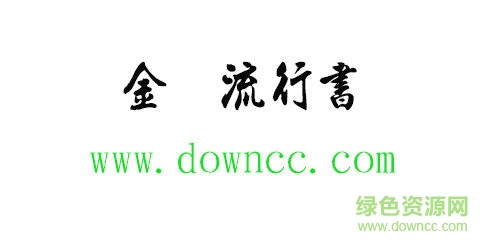
金梅流行書是一款適合于廣告設(shè)計印刷的電腦字體軟件,字體簡潔秀麗,一鍵安裝即刻使用,在你需要使用電腦編輯大量文章信息的時候,不妨使用一下該字體,能夠讓你的字體表現(xiàn)形式更加美觀大方哦,感興趣的可以來本站下載體驗一下。
金梅流行書是金梅字體庫中一種字體,常用于美工設(shè)計方面,喜歡的朋友不要錯過。
1、支持簡體中文和繁體中文。
2、支持網(wǎng)絡(luò)常用中文簡繁。
3、支持西文和數(shù)字。
4、字體風(fēng)格:時尚、現(xiàn)代、可愛、快樂、浪漫、女性、手寫風(fēng)、溫柔、休閑、優(yōu)雅、有趣
5、推薦場景:標(biāo)志、廣告、屏顯、書籍、影視、游戲